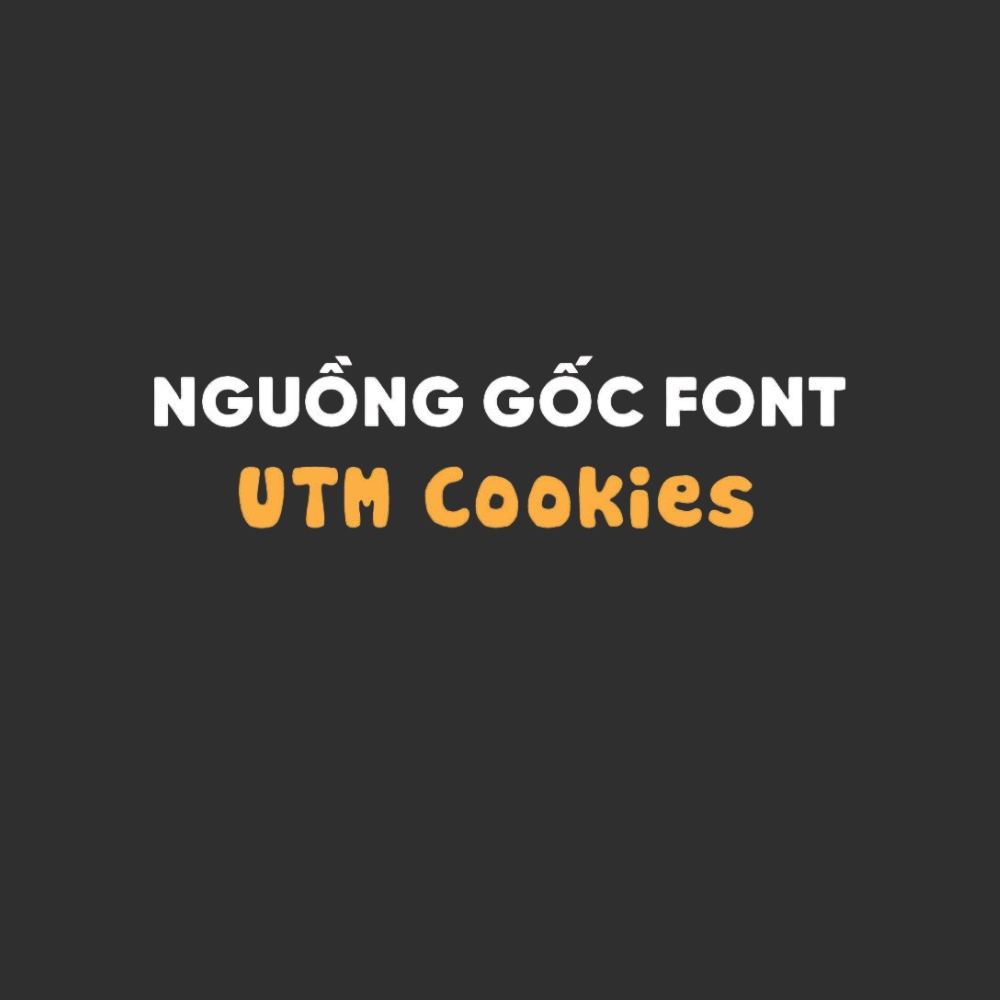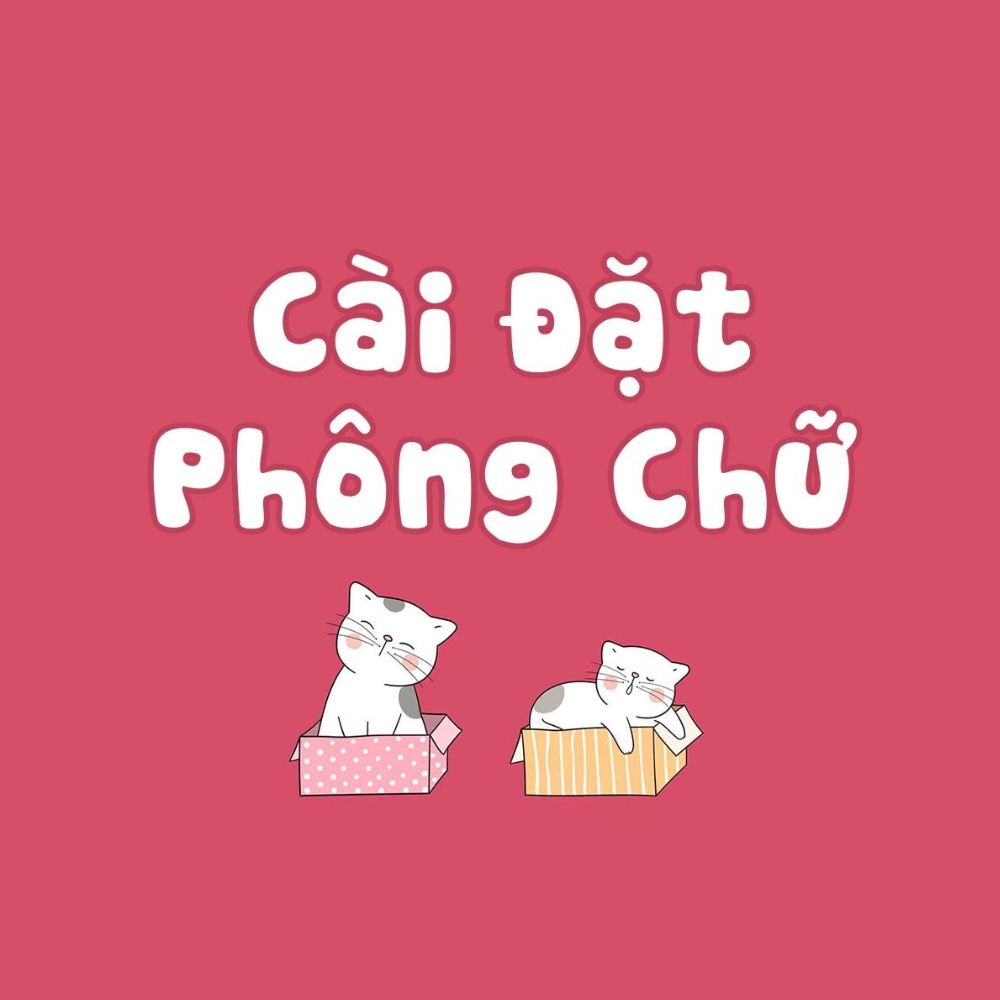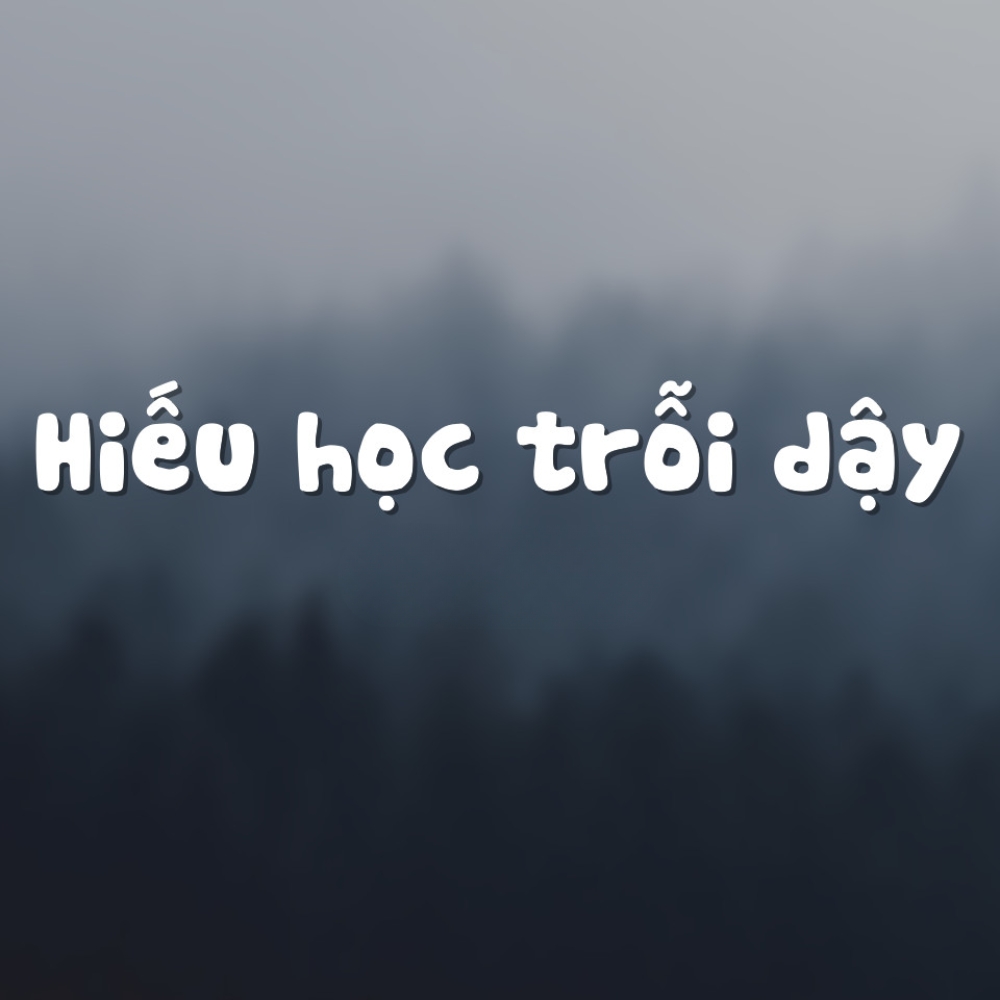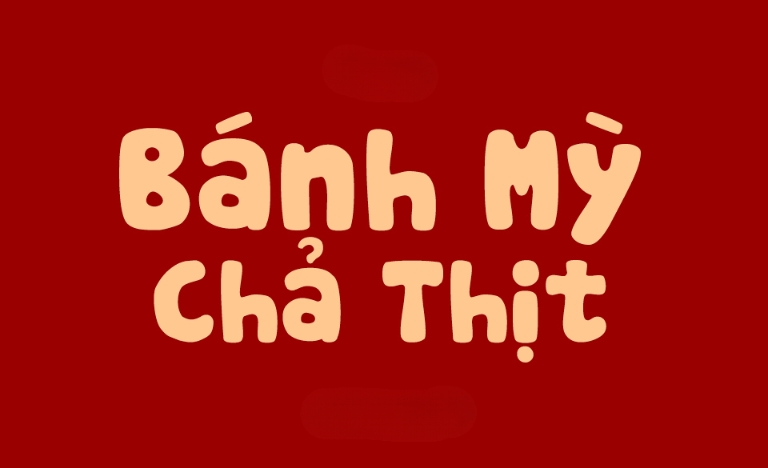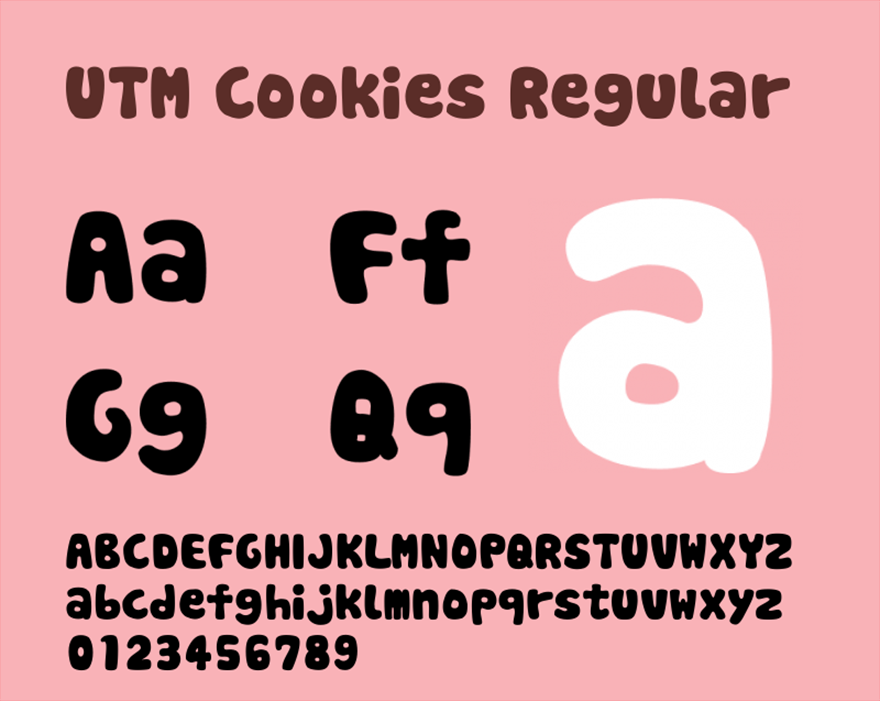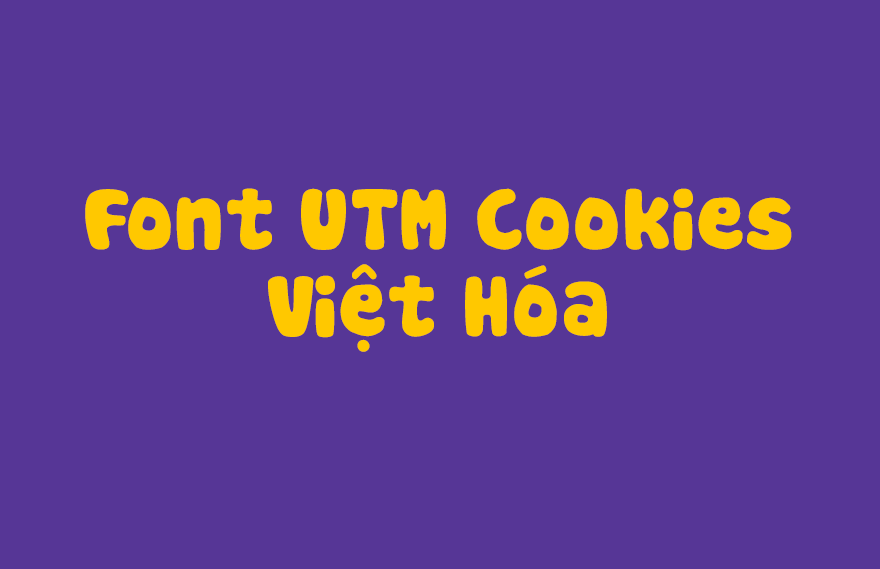
UTM Cookies là một bộ font chữ thuộc dòng viết tay mang phong cách đầy ngẫu hứng, gợi lên cảm giác thân thiện và gần gũi. Với những đường nét bo tròn, đầy đặn và vui tươi, bộ font này thường được ưu tiên cho các dự án thiết kế cần sự thoải mái, trẻ trung.
Khám phá nét cuốn hút của font UTM Cookies Việt hóa
Điểm nhận diện rõ nét của utm cookies font chính là cấu trúc chữ không quá gò bó, mô phỏng sinh động nét vẽ tay tự nhiên. Các ký tự được thiết kế với độ dày đồng nhất, loại bỏ cảm giác khô cứng của những kiểu chữ in ấn truyền thống, giúp bản thiết kế trở nên sinh động và có sức hút hơn. Bản Việt hóa giúp giải quyết các rủi ro về lỗi hiển thị ký tự đặc trưng, giúp dấu thanh phối hợp nhịp nhàng với thân chữ, duy trì vẻ đẹp nguyên bản của bộ gốc.
Sự ổn định của UTM Cookies còn thể hiện qua khả năng truyền tải năng lượng tích cực cho người xem. Khi được ứng dụng vào tiêu đề hoặc các đoạn trích dẫn ngắn, font chữ này tạo ra nhịp điệu thị giác lôi cuốn, giúp thông tin trở nên nổi bật mà vẫn rất dễ tiếp nhận. Đây là giải pháp phù hợp cho những ai đang tìm kiếm một kiểu chữ mang hơi thở hiện đại, năng động để hoàn thiện các ý tưởng thiết kế và sản phẩm sáng tạo của mình.
| Phân loại phong cách | Handwritten / Playful / Casual |
| Đặc tính hiển thị | Nét dày, bo tròn, nhịp điệu tự nhiên |
| Mục đích phù hợp | Tiêu đề, Poster, Menu cafe, Decor |
Gợi ý phối hợp: Do utm cookies việt hóa có cá tính mạnh và nét chữ khá dày, bạn nên phối hợp font này cùng một kiểu chữ không chân (Sans-serif) tối giản cho phần nội dung mô tả chi tiết. Sự kết hợp này giúp bản thiết kế đạt được sự cân bằng thị giác, khiến tiêu đề chính luôn nổi bật mà không gây rối mắt.
03 Ứng dụng của font UTM Cookies vào thực tế trang trí không gian
Với vẻ ngoài giàu tính thẩm mỹ và sự gần gũi, bộ font chữ này mang lại giá trị thực tế cao khi được đưa vào các hạng mục quảng bá và trang trí công trình hiện đại:
- Bảng nhận diện cho Homestay & Cafe: Những nét chữ tròn trịa của UTM Cookies rất ăn ý khi xuất hiện trên biển hiệu gỗ hoặc alu màu sắc tại các khu homestay container, nhà lắp ghép nghỉ dưỡng. Font chữ này giúp không gian toát lên vẻ mộc mạc và thân thiện đối với du khách.
- Thiết kế bao bì và quà tặng doanh nghiệp: Sử dụng font này cho các nhãn dán sản phẩm hoặc thiệp chúc mừng giúp thương hiệu tạo được ấn tượng về sự trẻ trung và tận tâm đối với khách hàng.
- Trang trí nội thất và Slogan tường: Bạn có thể dùng font Cookies để làm decal dán tường hoặc in tranh trang trí tại khu vực sảnh chờ, phòng ngủ nhà lắp ghép nhằm tạo điểm nhấn vui tươi cho không gian sống.
03 Lưu ý khi trình bày bố cục với bộ font UTM Cookies
Để khai thác hiệu quả vẻ đẹp của dòng font viết tay này mà không làm ảnh hưởng đến thẩm mỹ chung, người thiết kế nên lưu tâm một số điểm sau:
- Hạn chế viết hoa toàn bộ ký tự: Đặc trưng của font handwritten là sự nhịp nhàng giữa các chữ thường. Việc sử dụng toàn bộ chữ in hoa có thể làm cho tiêu đề trở nên thô cứng và gây khó khăn cho việc nhận diện mặt chữ.
- Kiểm soát khoảng cách dòng: Do cấu trúc chữ có phần đầy đặn, bạn nên để khoảng cách dòng thoáng một chút để các dấu tiếng Việt không bị chồng chéo lên nhau, giữ được sự minh bạch cho văn bản.
- Lựa chọn màu sắc rực rỡ: UTM Cookies phát huy hiệu quả thị giác cao khi phối cùng các tông màu nóng hoặc màu pastel sáng, giúp tôn vinh tinh thần năng động và vui vẻ của bộ chữ.